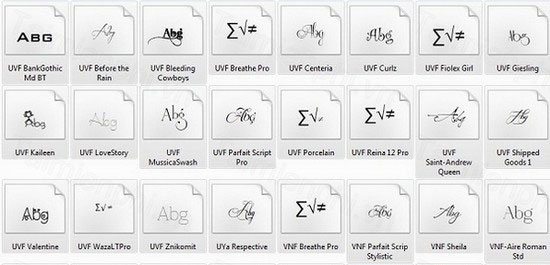
Việc lựa chọn font chữ phù hợp đóng vai trò quan trọng trong thiết kế đồ họa, góp phần tạo nên sự hấp dẫn và chuyên nghiệp cho sản phẩm cuối cùng. Một font chữ đẹp không chỉ dễ đọc mà còn truyền tải được thông điệp, cảm xúc và phong cách riêng biệt. Hiểu được điều đó, bộ sưu tập “61 Font Chữ Đẹp” ra đời, mang đến cho người dùng một kho tàng phong phú với 61 kiểu chữ độc đáo, đa dạng, sẵn sàng phục vụ cho mọi nhu cầu thiết kế.
Bộ font chữ này là một tập hợp các kiểu chữ được tuyển chọn kỹ lưỡng, đảm bảo chất lượng cao và tính thẩm mỹ vượt trội. Không chỉ dừng lại ở vẻ đẹp hình thức, bộ font này còn được tối ưu hóa để tương thích hoàn hảo với các phần mềm thiết kế đồ họa phổ biến và bộ gõ tiếng Việt Unikey và Vietkey, giúp người dùng dễ dàng thao tác và tạo ra những sản phẩm hoàn hảo nhất.
Sự Đa Dạng Về Kiểu Dáng và Phong Cách:
Bộ sưu tập “61 Font Chữ Đẹp” không chỉ đơn thuần là một tập hợp các font chữ thông thường. Nó là một kho tàng chứa đựng sự đa dạng về kiểu dáng và phong cách, từ những font chữ thanh lịch, hiện đại đến những font chữ mạnh mẽ, cá tính. Mỗi font chữ đều mang một vẻ đẹp riêng, đáp ứng được nhiều nhu cầu thiết kế khác nhau, từ thiết kế poster, áp phích, slogan cho đến các ấn phẩm quảng cáo, tạp chí hay website.
Bạn sẽ tìm thấy trong bộ sưu tập này những font chữ với đường nét mềm mại, uốn lượn tinh tế, tạo nên cảm giác nhẹ nhàng, thư thái. Bên cạnh đó, cũng có những font chữ với đường nét mạnh mẽ, góc cạnh sắc sảo, thể hiện sự năng động, hiện đại. Sự kết hợp hài hòa giữa các kiểu chữ khác nhau sẽ mang đến cho thiết kế của bạn một sức hút khó cưỡng.
Ứng Dụng Đa Năng Trong Nhiều Lĩnh Vực:
Bộ font chữ này không chỉ dành riêng cho các nhà thiết kế chuyên nghiệp mà còn phù hợp với tất cả những ai có nhu cầu sử dụng font chữ đẹp trong công việc và cuộc sống hàng ngày. Bạn có thể sử dụng chúng để:
Thiết kế đồ họa: Tạo ra những poster, áp phích, banner quảng cáo thu hút, ấn tượng. Những font chữ độc đáo trong bộ sưu tập sẽ giúp cho thiết kế của bạn trở nên nổi bật và khác biệt, thu hút sự chú ý của người xem.
Thiết kế website: Tối ưu hóa giao diện website, giúp cho nội dung trở nên dễ đọc, hấp dẫn hơn. Việc lựa chọn font chữ phù hợp sẽ tạo nên sự chuyên nghiệp và tinh tế cho website của bạn.
Thiết kế ấn phẩm: Tạo ra các ấn phẩm như brochure, catalogue, tạp chí với giao diện đẹp mắt, chuyên nghiệp. Bộ font chữ này sẽ giúp cho các ấn phẩm của bạn trở nên thu hút hơn, thu hút sự chú ý của khách hàng.
Viết lách và biên tập: Sử dụng những font chữ đẹp để tạo nên những tác phẩm viết lách ấn tượng, thu hút người đọc. Việc lựa chọn font chữ phù hợp sẽ làm tăng tính thẩm mỹ và khả năng truyền tải thông điệp của văn bản.
Ứng dụng chat và mạng xã hội: Tạo nên những dòng tin nhắn, bài đăng trên mạng xã hội nổi bật và thu hút sự chú ý.
Tính Năng Nổi Bật Của Bộ Font Chữ Đẹp:
- 61 font chữ đẹp mắt: Sự đa dạng về kiểu dáng, phong cách đáp ứng mọi nhu cầu thiết kế.
Phân loại tiện lợi: Các kiểu font chữ cùng loại, khác tính chất được xếp chung vào một nhóm, giúp người dùng dễ dàng tìm kiếm và sắp xếp.
Kết Luận:
Bộ sưu tập “61 Font Chữ Đẹp” là một lựa chọn hoàn hảo cho những ai đang tìm kiếm những font chữ đẹp, chất lượng cao và đa dạng để phục vụ cho công việc thiết kế của mình. Với sự đa dạng về kiểu dáng, phong cách và tính năng vượt trội, bộ font chữ này sẽ giúp bạn tạo ra những sản phẩm thiết kế ấn tượng, chuyên nghiệp và thu hút mọi ánh nhìn. Hãy tải xuống bộ font chữ này ngay hôm nay và trải nghiệm sự khác biệt!